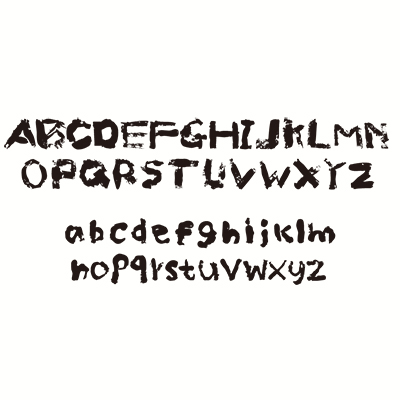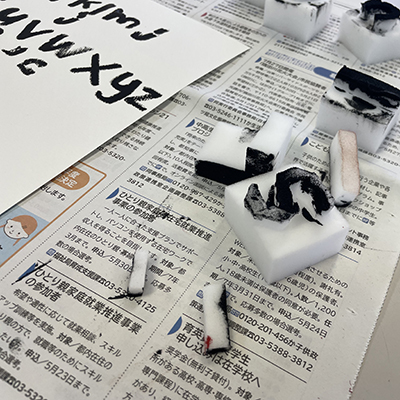
ガチガチフォント
不揃いが生む個性派フォント
上手くできた!(Y.M.)
今回はスポンジを使って文字を作ってみました。スポンジを文字のパーツにカットして、絵の具をつけて紙に押すことで、迫力のある表現になったと思います。このフォントは、インパクトのあるタイトルに使えるようにデザインしました。ポスターなどに活用できると思います。(HOULU)
このメンバーは、なんと今回は初めてフォントにチャレンジ。いつも集中している時間が短い方ですが、最後まで自分なりに考えながら取り組む事ができた作品です。(のぞみ作業所)